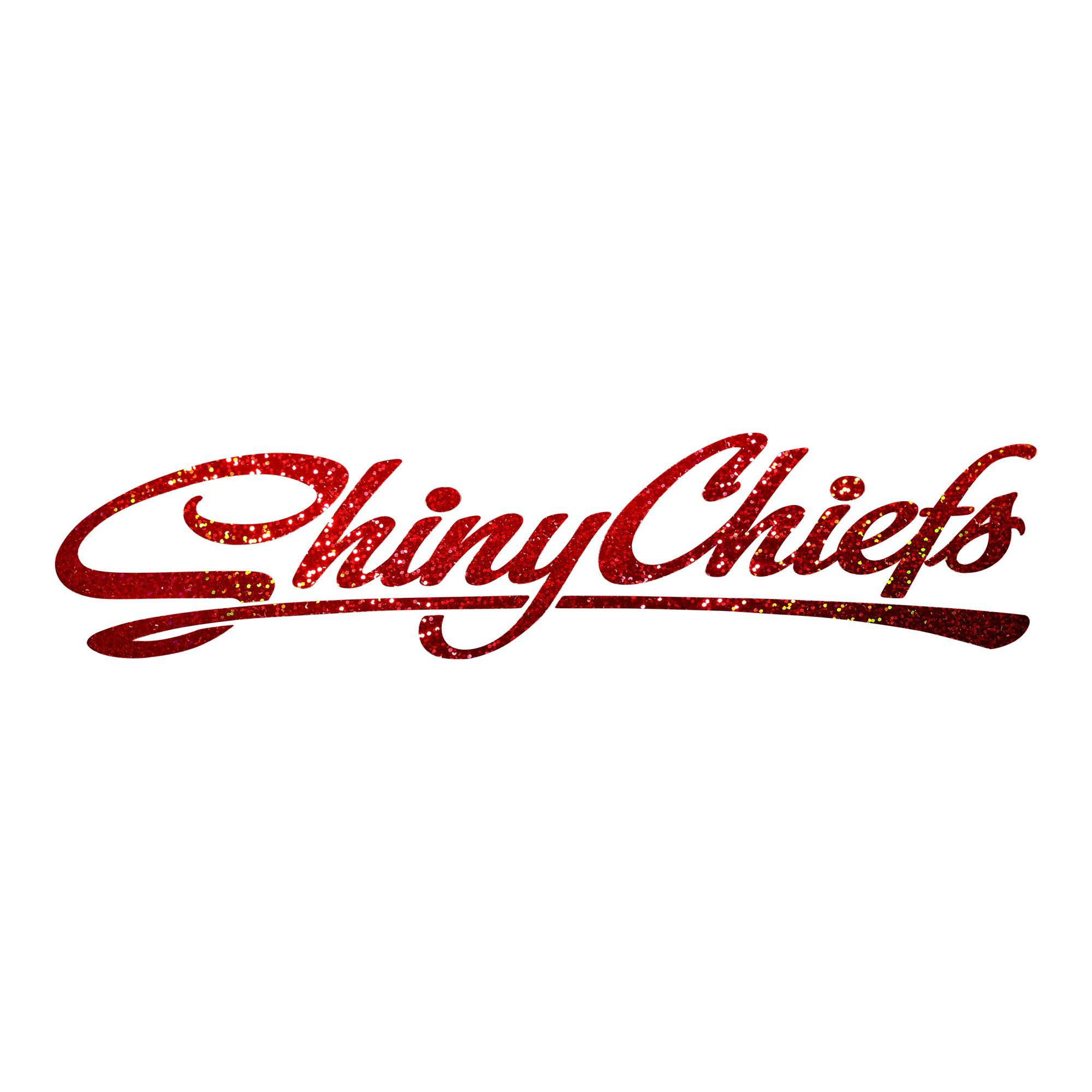
suche diese Schriftart vom Bild (ShinyChiefs)
könnt ihr mir helfen? Ich suche diese Schriftart von diesem Bild. Habe leider keine Infos oder ähnliches zu der Schriftart 😞
Aber vielleicht zu dem Bild:-?
Googeln hätte ich wohl auch können – es ging mir ja eher ums Prinzip, das gleich erklärt wird, wo das Bild herkommt, ohne dass jeder einzelne von uns der helfen will erstmal suchen muss.
Der Link hilft mir aber auf die Schnelle auch nicht weiter … Mann müsste das schwarze Logo von der Website nehmen, die Buchstaben trennen und WTF füttern. Das ist mir aber am Tablet zu umständlich …
:tuschel: Führt auch leider zu nix …
Könnte auch gezeichnet sein und die gleichen Buchstaben wurden dann kopiert. Das S hätte ich eh gedacht, dass es zumindest modifiziert ist …
Zumindest ähnlich:
Mir kommt das s bekannt vor, aber ich komme nicht drauf ...